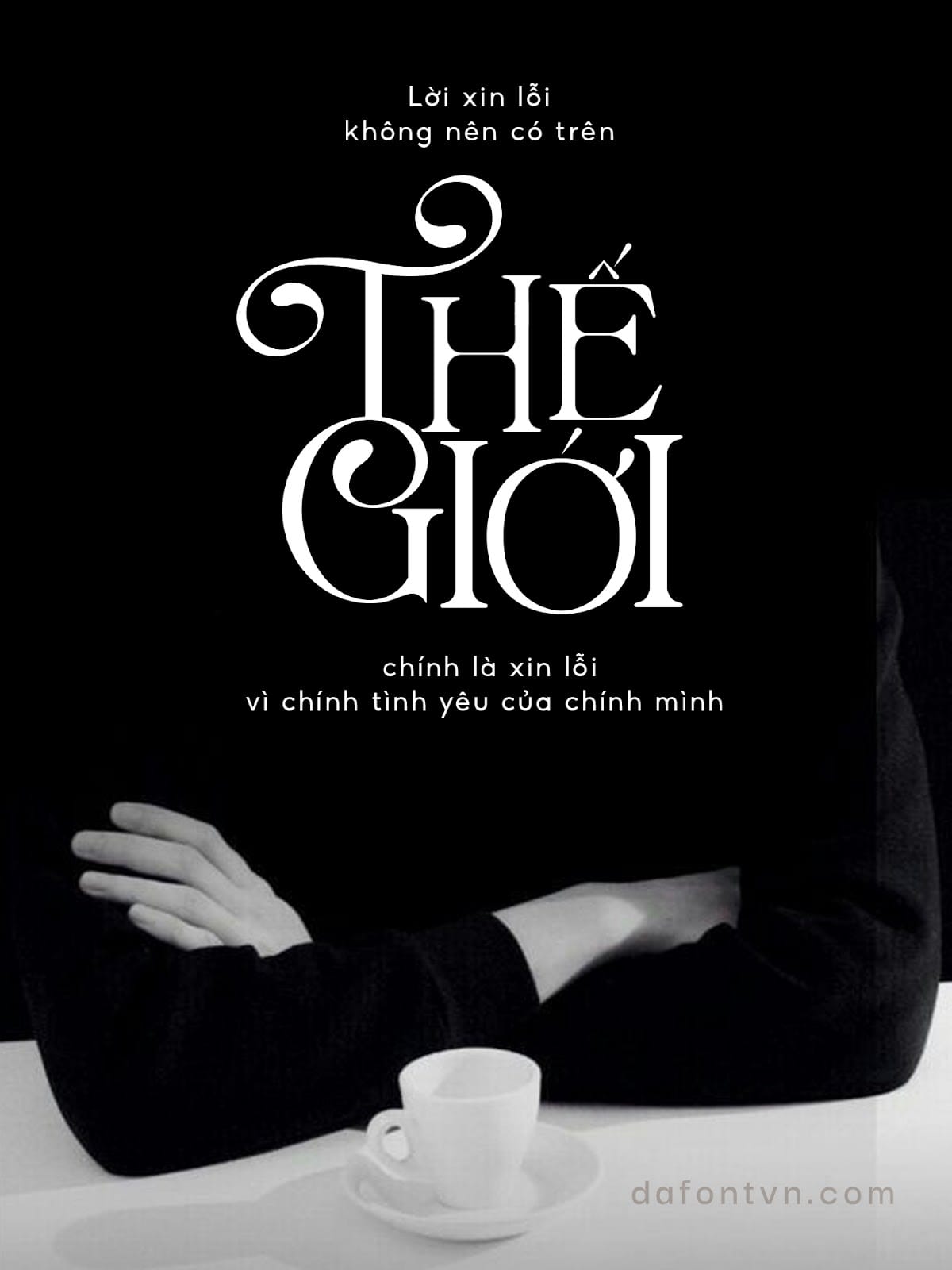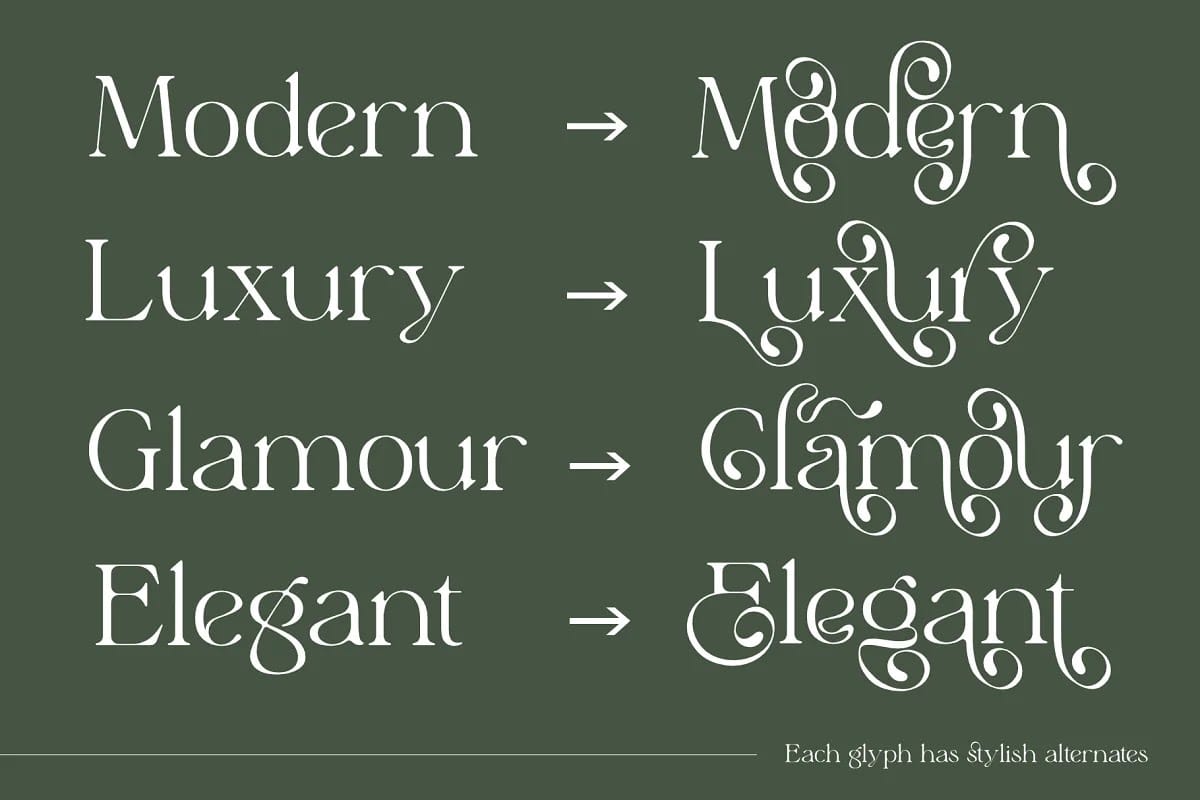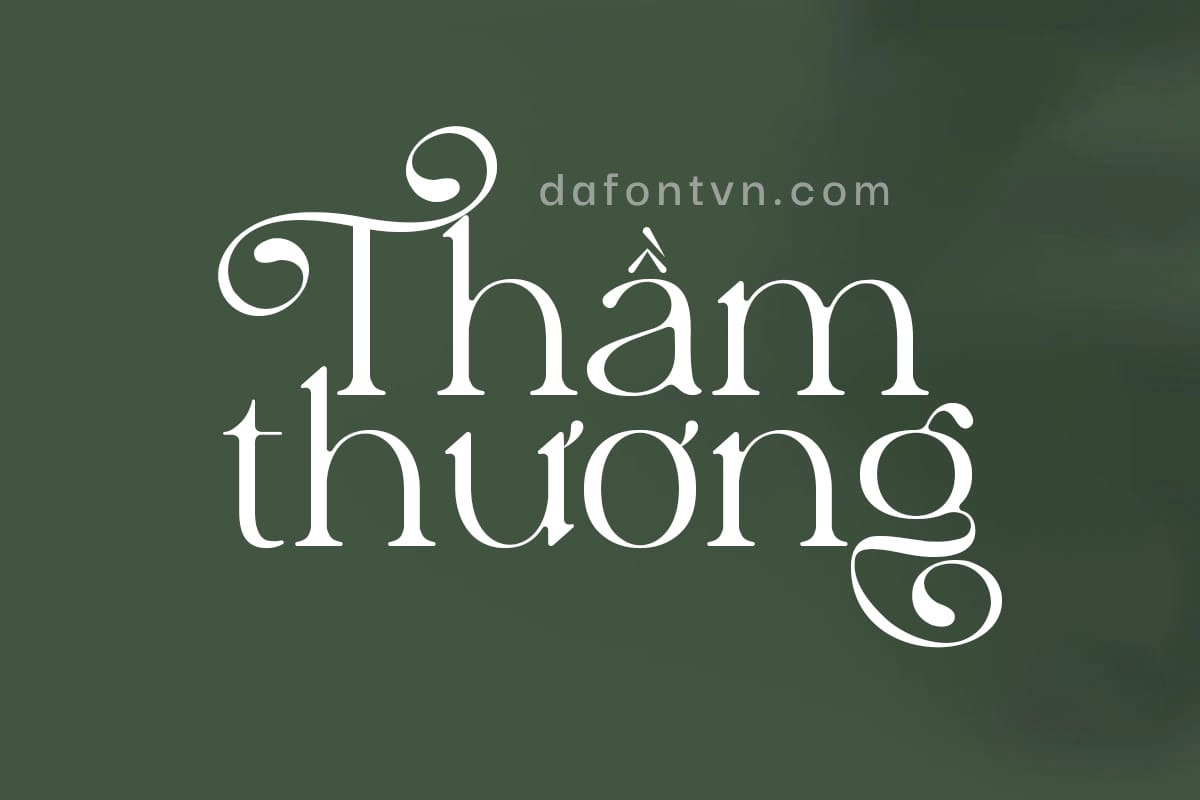
Elyaris là một font chữ hiện đại, mới mẻ và độc đáo có rất nhiều glyph cực đẹp để bạn có thể sử dụng tạo ra các thiết kế ấn tượng hơn. Phù hợp cho nhiều thiết kế khác nhau như bìa truyện, tạp chí, typography, quotes, tiêu đề…
Font Elyaris việt hóa có 15 chữ ghép và 89 chữ thay thế bao gồm chữ hoa và chữ thường, font được việt hóa đầy đủ, chỉnh sửa lại 1 số chi tiết và tối ưu lại font để sử dụng dễ dàng trên bất kỳ phần mềm nào.